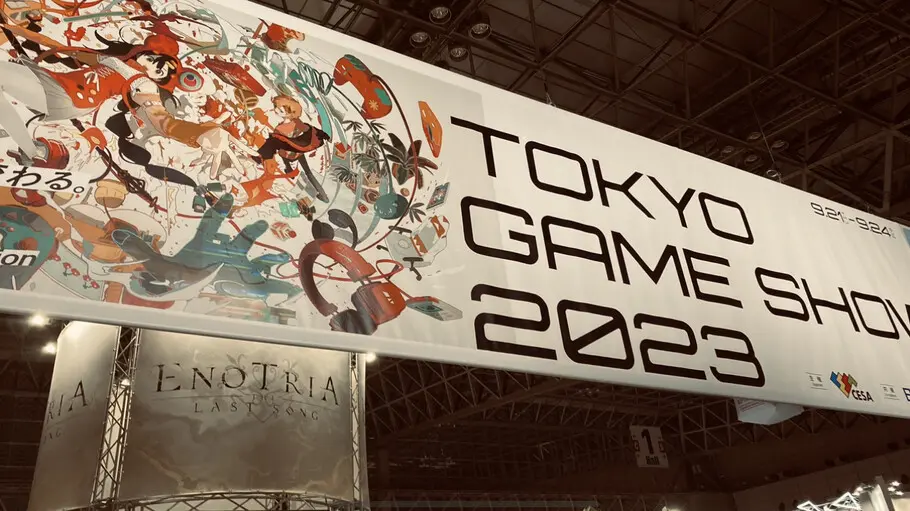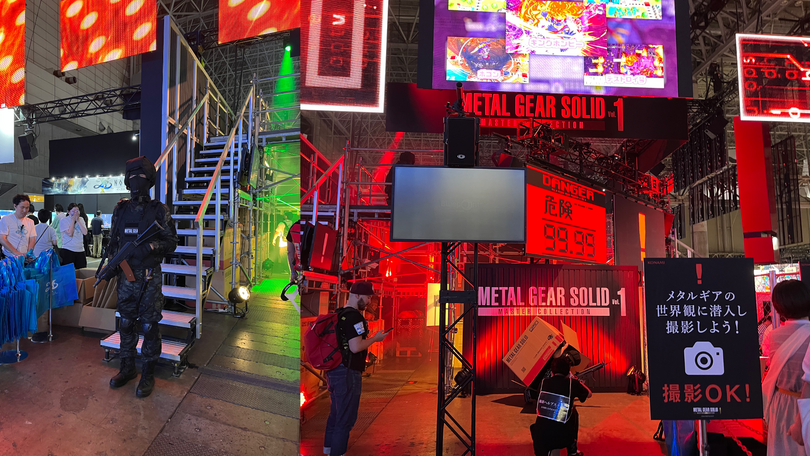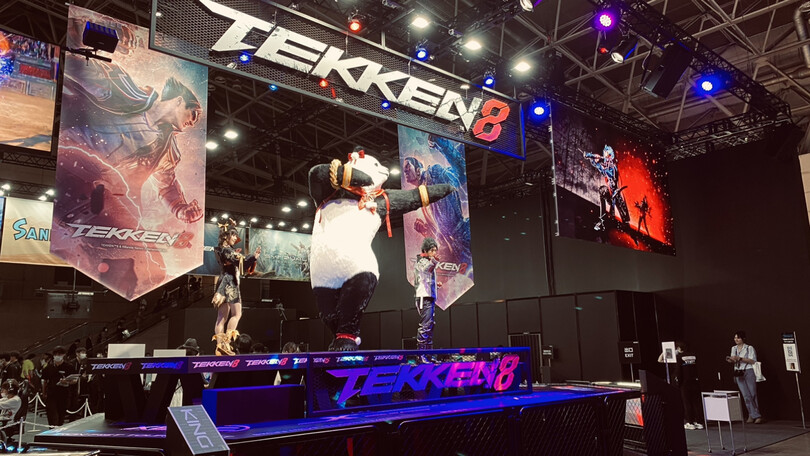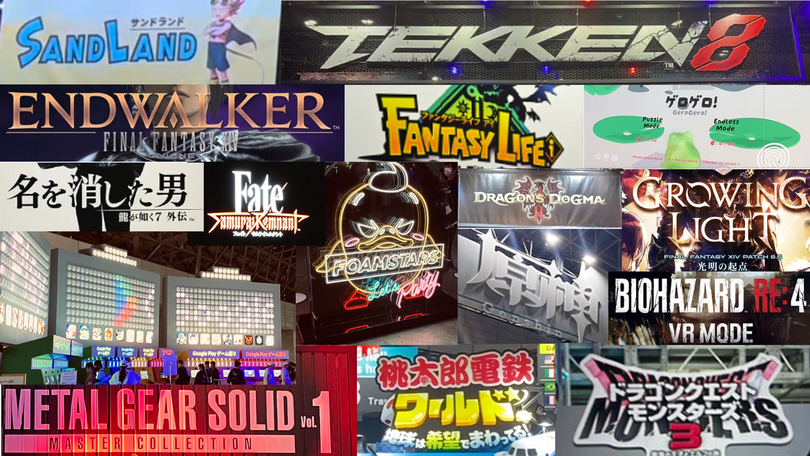
フォント会社の視点から見たゲームショウ【TGS2023】
東京ゲームショウ2023(TGS2023)が、9月21日から24日の4日間開催されました。4年ぶりに完全開催となった幕張メッセの全展示ホールを使って、過去最多の44カ国の地域から787の企業や団体が出展。「ゲームが動く、世界が変わる。」をテーマに様々な角度からアプローチされた展示には国内外の多くの来場者でにぎわっていました。
東京ゲームショウではこのイベントに合わせて新作が発表され、未発売のタイトルを試遊でき、ゲームの世界観を肌で感じることができるような体験型ブースが多く存在。特に大手企業のブースには、大がかりなフォトスポットが目を引きました。
ビジネスデイでも120分待ちの試遊コーナができていた「メタルギアソリッド マスターコレクションVol. 1」隣には、作品を体感できるフォトスポットも展示。
とあるゲーム会社のクリエーターを担当している方と話す機会があり、ゲームを制作する中でのフォント選びについても話してくれました。「限られた予算の中でフォント選びはとても骨の折れる作業。ゲームの世界観やキャラクターの個性が出るような雰囲気を持ったフォントを選べるよう心がけています。」その会社では、ゲーム制作過程の中で、全体が把握できるようになる終盤の段階で、フォント選びの作業を行なっているようでした。
2024年発売予定の「鉄拳8」の参戦キャラクターとなったパンダが注目を集めていました。
特に、シリーズ化されているゲームでは、ロゴも時代と共に変化していきます。新しいシリーズはどういったターゲットでどのようなブランディングを作り上げファンを魅了していくのか、とても重要です。これまでと大きくイメージを変えずに今に合うよう刷新していかなくてはいけません。写真はTEKKEN8のブース。今回新しいキャラクターも参戦し、より力強い格闘ゲームのイメージが伝わります。
今回の展示で、ゲームタイトルのロゴや使用されている文字を集めました。
ビジネスソリューションというブースには、ゲームに関連する多種多様な企業が出展。ワンストップで多言語に対応できる会社やゲームのデバックのサービスを提供する会社、ゲーム制作の環境づくりに対応する製品やサービスに特化した会社など日本以外を拠点とする企業も多く参加していました。
多言語でのローカライズ、グローバル展開の中にはどの言語に翻訳しても雰囲気を崩すことなく統一した世界観を保つことはゲーム業界も同じ。来場者や出展企業の傾向からも、さらに今後加速していく事業なのではと感じました。